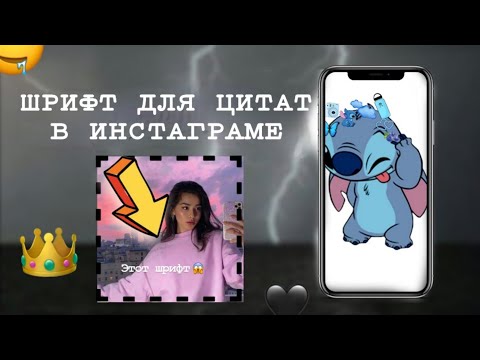
5 советов по выбору красивого шрифта для цитат
Шрифты играют важную роль в создании эффектного дизайна, особенно когда дело касается цитат. Чтобы подобрать шрифт, который будет идеально сочетаться с вашими цитатами и придавать им элегантность, обратите внимание на следующие советы:
Учитывайте основную идею цитаты при выборе шрифта. Если цитата имеет юмористический уклон, подойдет веселый и нестандартный шрифт. А если цитата направлена на вдохновение, выбирайте элегантные и стильные шрифты.
Используйте контрастные комбинации шрифтов. Для заголовков можно выбрать более крупные и выразительные шрифты, а для основного текста - более простые и читаемые шрифты.
Играйте с размерами и выравниванием. Экспериментируйте с размерами шрифта, чтобы создать эффектные акценты. Также обратите внимание на выравнивание текста - выравнивание по центру, по правому или левому краю может изменить восприятие цитаты.